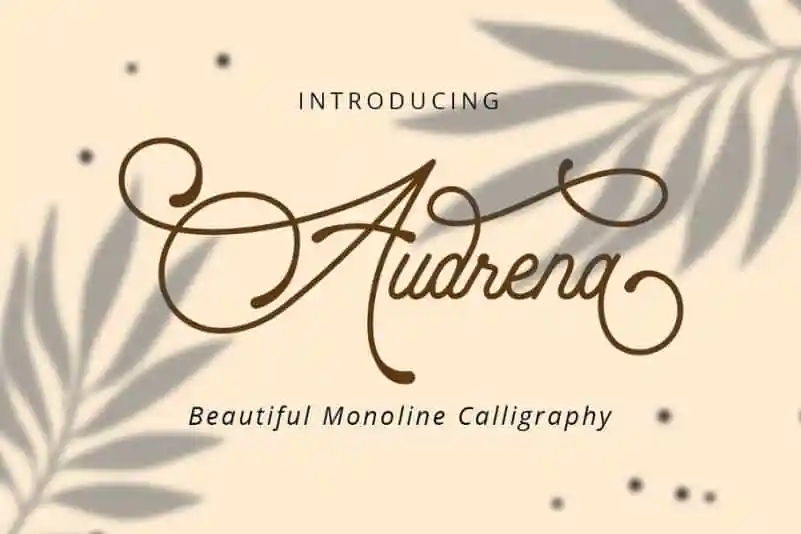
Audrena Script Font – Fonte Grátis
Audrena Script Font
A Audrena Script é uma elegante fonte criada para designers que buscam algo sofisticado e encantador para seus trabalhos. Esta nova opção moderna de script vem diretamente do talentoso designer PutraCetol Studio. Ideal para personalizar logotipos, papelaria e até mesmo festas de casamento, como cartões de convidados e convites. Com suas linhas leves e suaves, a Audrena oferece uma sensação confortável para quem está sempre buscando um toque a mais na criação visual. Seja para textos importantes em sua logo ou simples mensagens no seu Instagram, esta fonte é perfeita para estilos variados de design digital como blogs pessoais, sites ou redes sociais. O design da Audrena traz uma sensação romântica e delicada que certamente vai agradar os designers gráficos que procuram um toque personalizado para seus trabalhos.